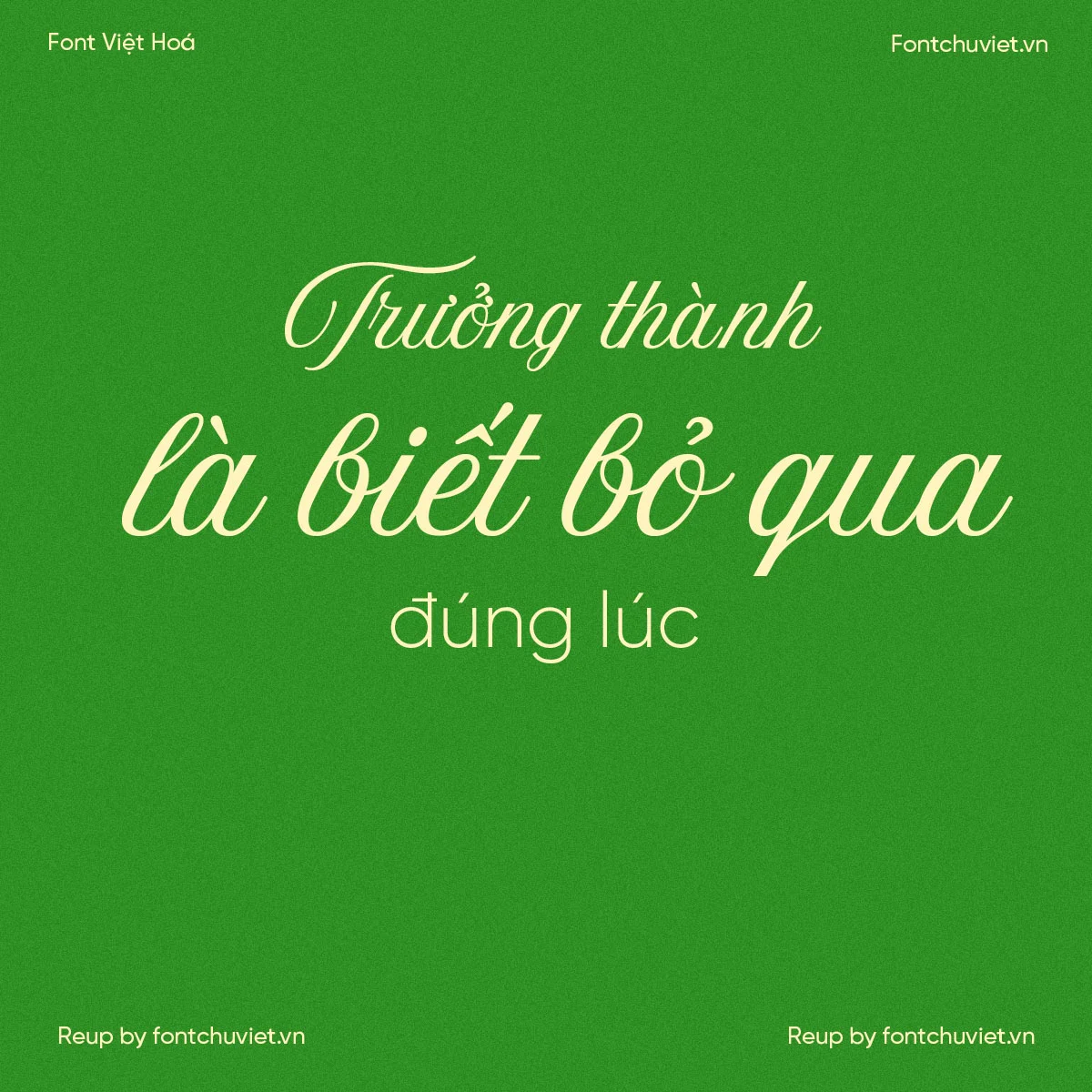
Font VL Aurora – Font Việt hoá
Cỡ chữ: 60px Aa aa AA Thử font Việt hoá 1234567890 0/300 Gõ văn bản bên dưới để xem trước font chữ ◪ View Glyphs Font VL Aurora – Font Việt hoá là một font chữ nghiêng tinh tế, có thể dùng cho sách báo, tên của học viên hoặc tên của người được khen … Đọc tiếp Font VL Aurora – Font Việt hoá